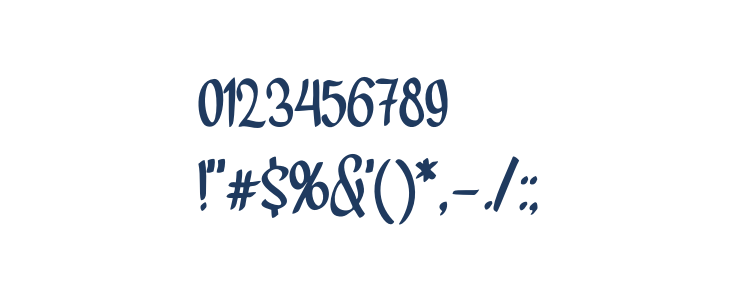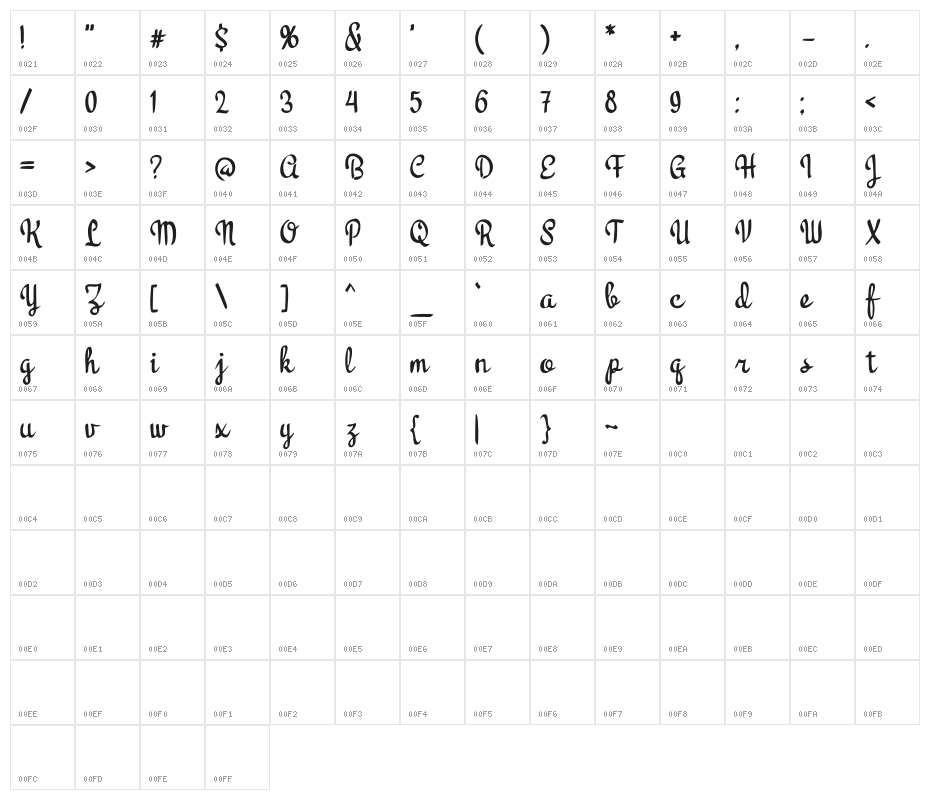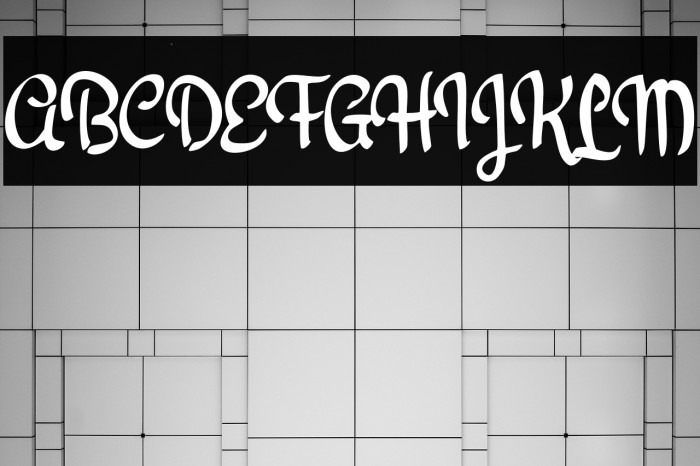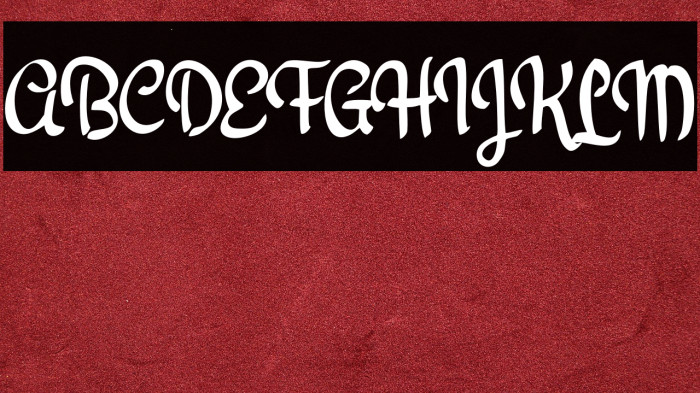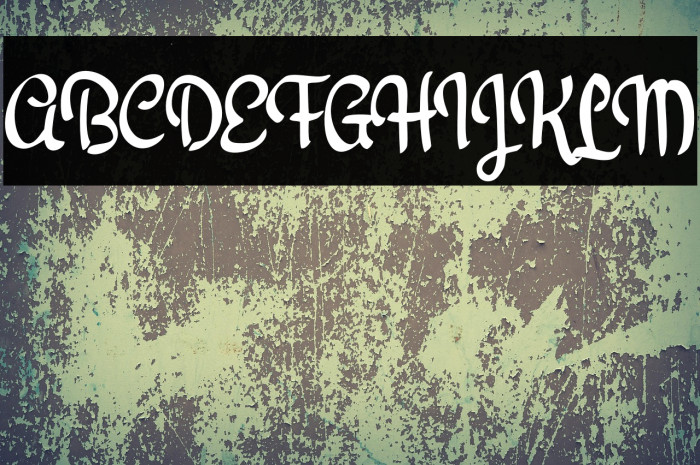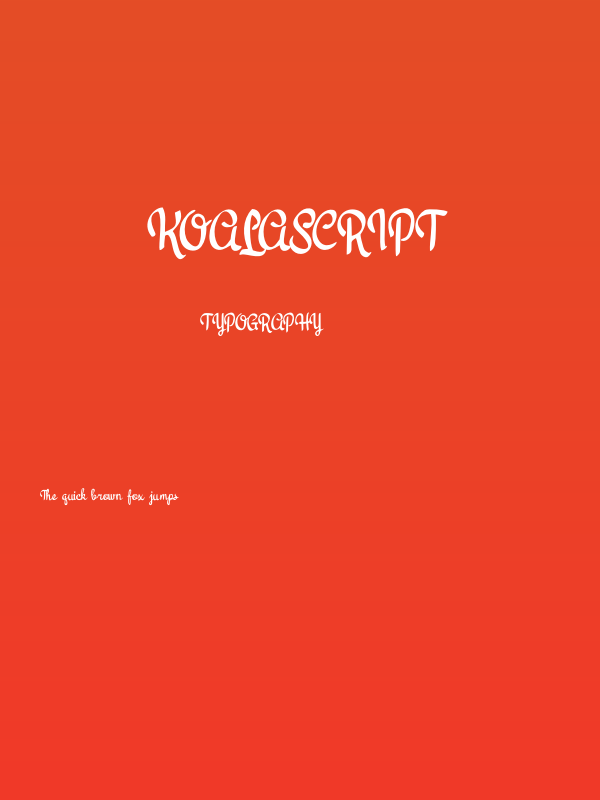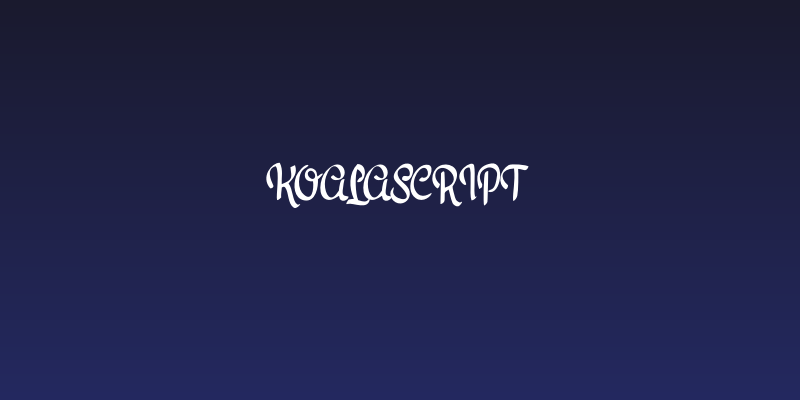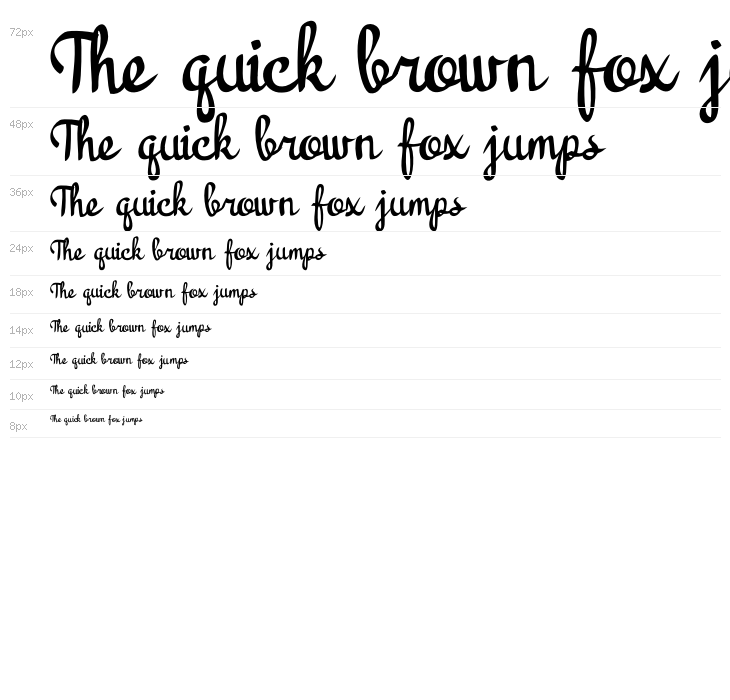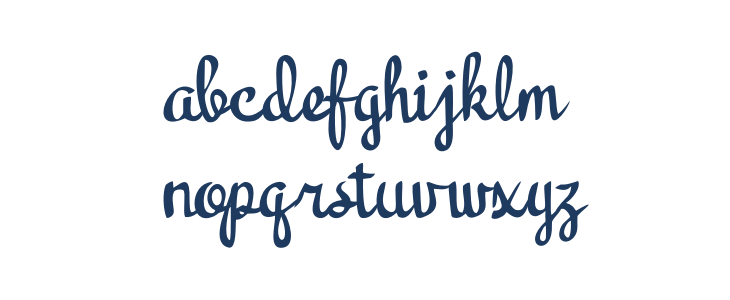
KoalaScript Font
| Stile generale | Modern, Decorative |
| Caso d'uso | Logos, Headlines, Invitations |
| Progetti proposti | Ideal for creative projects such as invitations, greeting cards, branding, and playful logos. |